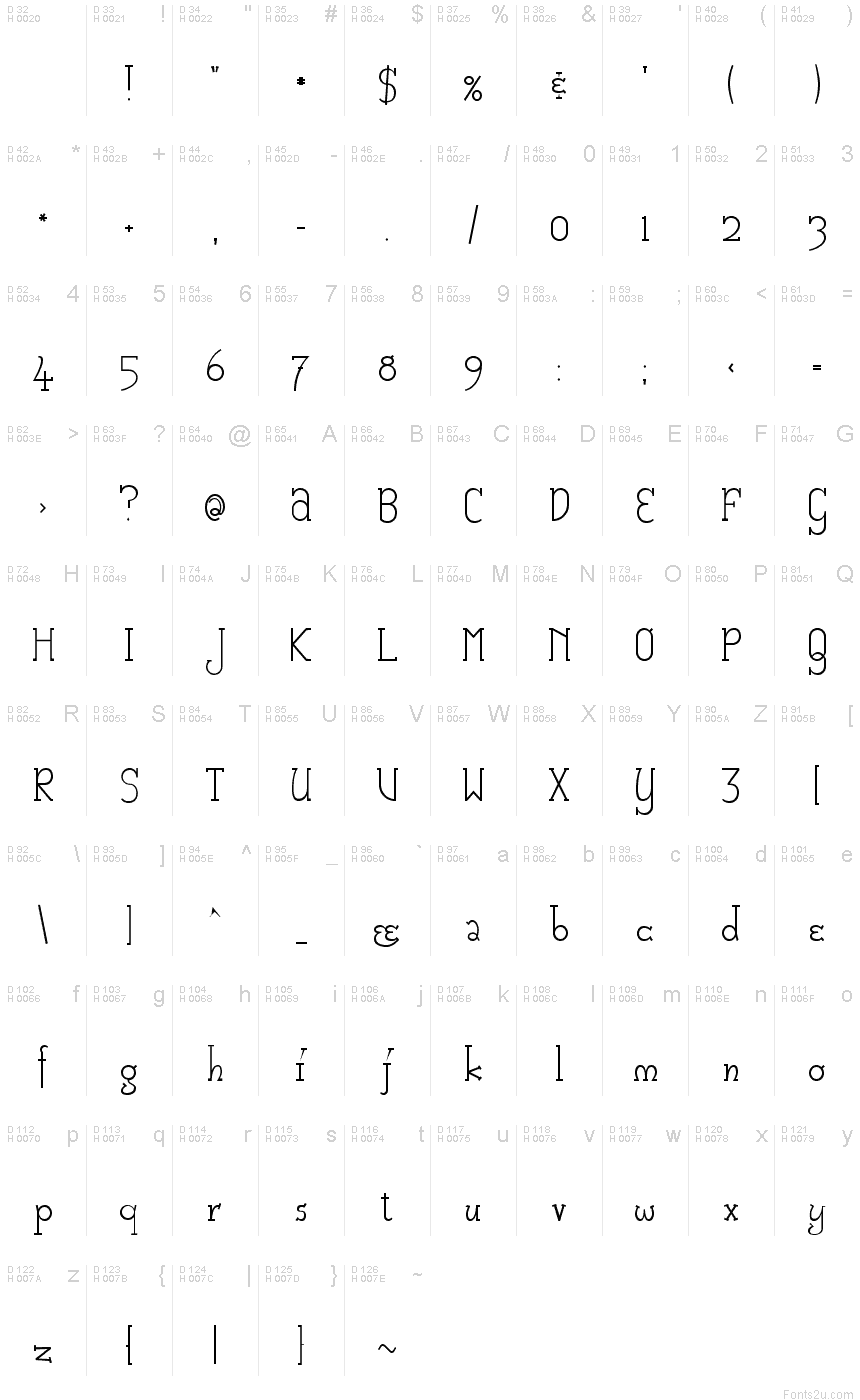
Catharsis Macchiato
Krój pisma Catharsis Macchiato autorstwa Christiana „Catharsis” Thalmanna to bezpłatny, dekoracyjny font, który przekuwa elegancką kaligrafię w coś zabawnego i nietuzinkowego. Jego giętkie pociągnięcia układają się w delikatne pętelki, a wyraziste akcenty i finezyjne zakończenia nadają każdemu słowu niemal teatralnego wdzięku. Litery sprawiają wrażenie odręcznie kreślonych, z nutką psoty – niczym notatki na marginesie ulubionej powieści fantasy czy etykiety na tajemniczych buteleczkach aptecznych.
Dzięki Catharsis Macchiato uzyskasz rytm zbliżony do pisma ręcznego, nie tracąc przy tym na czytelności, co świetnie sprawdza się w projektach okładek książek, baśniowych tytułów, menu kawiarnianych, opakowań rzemieślniczych, zaproszeń czy oryginalnych logotypów. Ten darmowy font najlepiej prezentuje się w większym rozmiarze, pozwalając wybrzmieć jego nietypowym krzywiznom. Dla zachowania równowagi, zestaw Catharsis Macchiato z prostym, neutralnym krojem bezszeryfowym w tekście głównym lub podpisach.